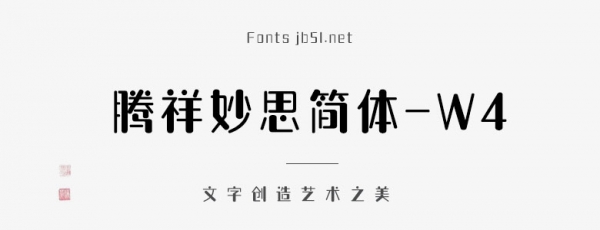
騰祥妙思簡體-W4是一款不錯的藝術(shù)字體,由騰祥字庫出品,筆畫斷連輾轉(zhuǎn),粗細(xì)藏露變化,相映成趣,字形俊雅,風(fēng)格獨(dú)特,是該系列字庫中最粗一款,適合應(yīng)用于藝術(shù)設(shè)計、平面宣傳設(shè)計、網(wǎng)頁設(shè)計,書法字帖等領(lǐng)域,需要的朋友可以前來本站下載。
此款字風(fēng)格為美術(shù)字體。妙思W4為系列字庫中最粗一款,適用于標(biāo)題、小標(biāo)題等。筆畫斷連輾轉(zhuǎn),粗細(xì)藏露變化,相映成趣;字形俊雅,風(fēng)格獨(dú)特;筆畫凝練簡潔巧妙構(gòu)思、字形結(jié)構(gòu)修長、整幅字給人以樸實(shí)無華,清新秀麗之感。設(shè)計師以輕松的筆調(diào)詮釋出整款字體的風(fēng)韻,筆畫聚散有致,沉靜閑適,妙語空傳醉墨香……